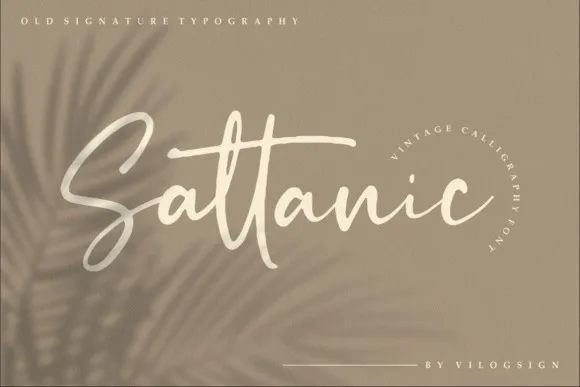
Sattanic Script Font – Fonte Grátis
Sattanic Script Font
Olá a todos! Estou aqui para compartilhar com vocês uma nova adição à nossa coleção de fóntes, Sattanic Script Font. Esse é um belo script font que combina elegância e originalidade em proporções equilibradas para se adequar tanto a projetos modernos quanto vintage. Como seu nome sugere, Sattanic Font é uma nova assinatura de texto de mão escrita, mas também contém alternativas estilísticas, ligaturas e swashes que adicionam um toque elegante aos seus design. Com essa fóntes, você pode criar logos atraentes, tags, modelos, rótulos, adesivos e até mesmo textos em destaque, aproveitando-a para outdoor publicidade, identificação de marca e muito mais. Adote Sattanic Script Font para dar um toque moderno e profissional aos seus futuros projetos. Seu design ficará ainda mais atraente com essas alternativas estilísticas, ligaturas e swashes. Esta fonte é perfeita tanto para designers de nível básico quanto para profissionais que buscam um diferencial em suas criações. Porém, se você deseja uma experiência ainda mais incrível, Sattanic Font também oferece o benefício adicional do designer M.0Type, garantindo a qualidade e precisão necessária para qualquer projeto que você possa estar realizando.